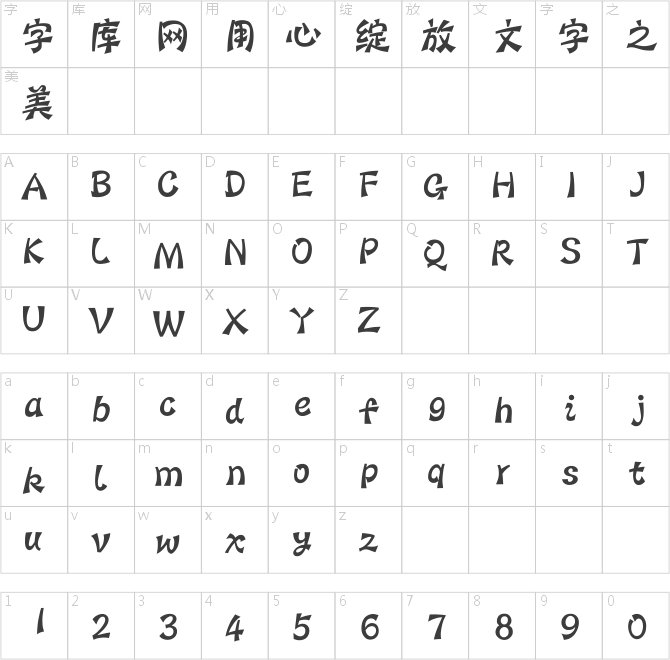
字體名稱: 迷你簡(jiǎn)蝶語
迷你簡(jiǎn)蝶語
迷你簡(jiǎn)蝶語介紹
迷你簡(jiǎn)蝶語字體字庫是一款讓人賞心悅目、百看不厭的中文字體,適合各類廣告和產(chǎn)品包裝設(shè)計(jì)應(yīng)用,字體大小3.23MB,格式為ttf字體,上傳用戶是釜源貿(mào)易,作者/版權(quán)方為疑似偽造